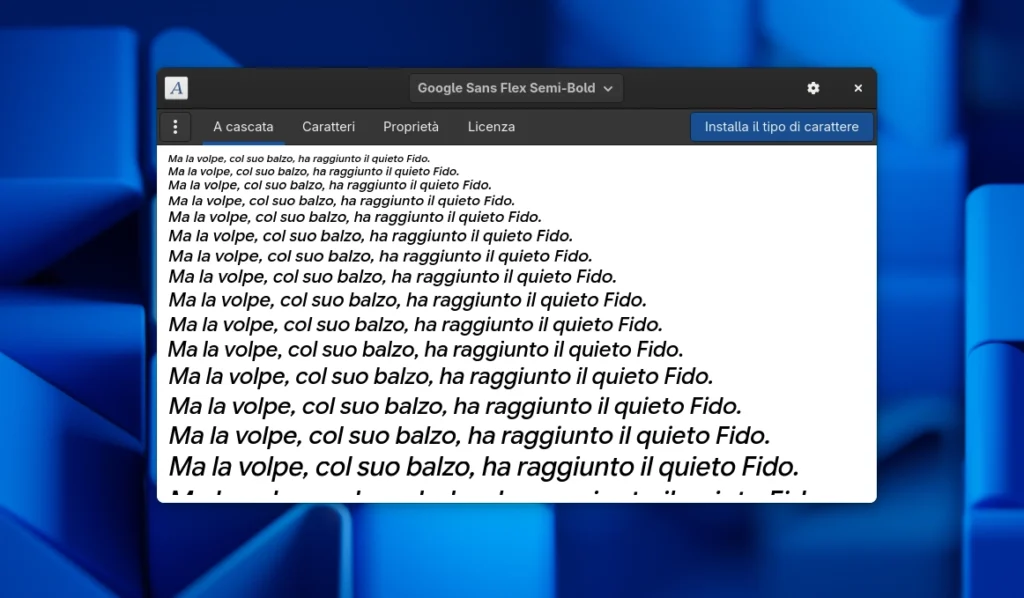
Google Sans Flex Rilasciato Open Source: La Nuova Font Variabile di Google Arriva su Linux
Google ha compiuto un passo significativo nel mondo della tipografia open source rendendo disponibile la sua font di nuova generazione, Google Sans Flex.
Definito il typeface ufficiale per il marchio Google, Google Sans Flex è un sans serif moderno, completamente riprogettato per l’uso ottimale su schermi e sistemi operativi digitali. Questa decisione di rilasciare la font sotto la SIL Open Font License (OFL) è una notizia eccellente per la comunità Linux, in particolare per gli utenti di Ubuntu, che ora possono installarla e utilizzarla per rinfrescare l’aspetto del proprio desktop.
L’Architettura Variabile Dietro il Nome “Flex”
Il nome “Flex” non è casuale: si riferisce al fatto che Google Sans Flex è una font Variabile. Sviluppata da David Berlow, questa font è stata ricostruita da zero come una font multi-asse, estremamente flessibile. Gli assi variabili che la caratterizzano includono weight (peso), width (larghezza), optical size (dimensione ottica), slant (inclinazione) e un asse dedicato per i rounded terminals (le estremità arrotondate dei caratteri).
Queste assi variabili rappresentano un grande vantaggio creativo per gli sviluppatori Android e web designer, consentendo un design “espressivo” con un singolo file di font. Sebbene gli ambienti desktop Linux attuali non sfruttino ancora appieno tutte le capacità dinamiche delle font variabili, Google Sans Flex funziona comunque in modo impeccabile come una font UI elegante e competente, offrendo un aspetto di alta classe, specialmente sui display HiDPI con scaling frazionario.
Un Semplice Tweak per Cambiare il Look di Ubuntu